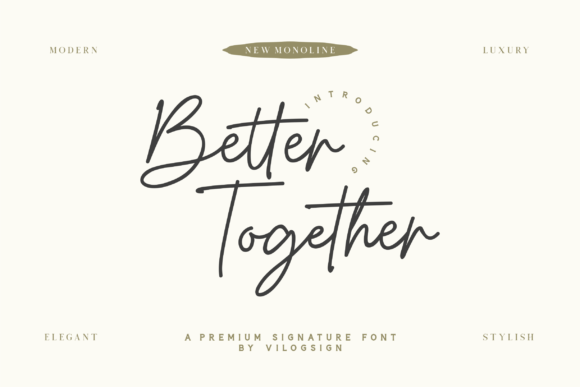
Better Together
์ •๋ฐ€ํ•˜๊ฒŒ ์ œ์ž‘๋œ Better Together๋Š” ๊น”๋”ํ•œ ๋ฒกํ„ฐ, ๋ถ€๋“œ๋Ÿฌ์šด ํƒ€์ดํฌ๊ทธ๋ž˜ํ”ผ ๋ฐ ์•ˆ์‹ฌํ•  ์ˆ˜ ์žˆ๋Š” ์ƒ์—…์šฉ ๋ผ์ด์„ ์Šค๋ฅผ ์ œ๊ณตํ•ฉ๋‹ˆ๋‹ค.